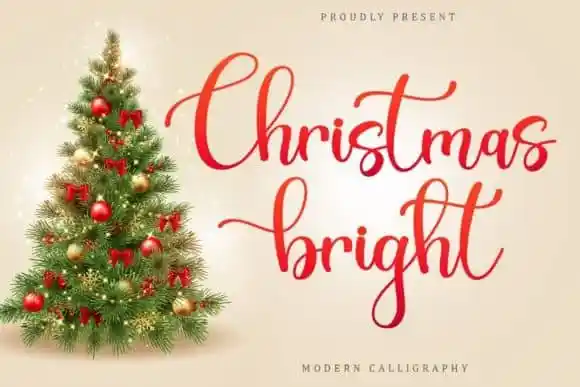
Christmas Bright Calligraphy Font – Download Grátis
A Christmas Bright Calligraphy Font é uma obra-prima para todos os designers apaixonados por festas natalinas. Com seu estilo moderno e fina estética tanto no início quanto na conclusão, esta fonte se destaca como perfeita para diversas necessidades de design. Alif Ryan Zulfikar criou este tipo de letra com um toque elegante e casual, tornando-o perfeito não apenas para festas natalinas, mas também para cartas de Natal. Seus traços delicados e ascentes suaves trazem uma sensação de acolhimento ao seu design. Esta fonte foi projetada e compartilhada por Alif Ryan Zulfikar e é perfeita para personalizar seus projetos festivos ou suas cartas natalinas, oferecendo um toque definitivamente encantador. Com PUA (Proprietary Unicode Area) encoded, você terá fácil acesso a todos os traços e ascentes desta fonte, criando uma variedade de opções para dar vida à sua arte digital. Com o Christmas Bright Calligraphy Font na sua lista de fontes favoritas, seus designs natalinos sempre serão um pouco mais especializados e encantadores.